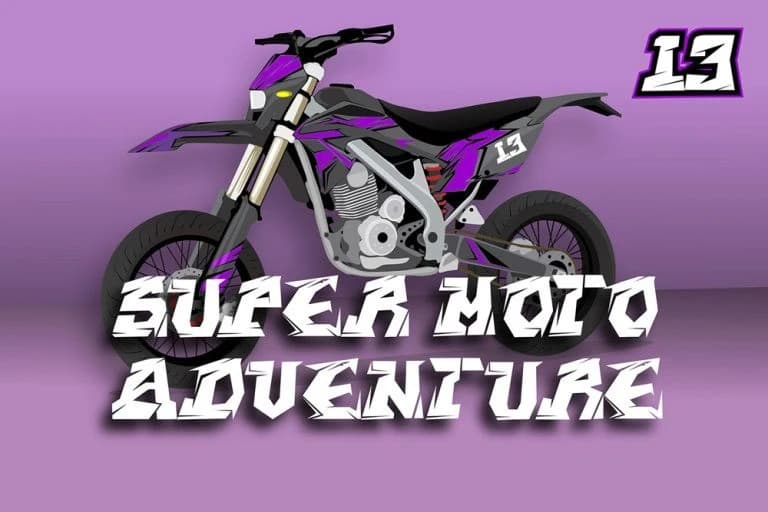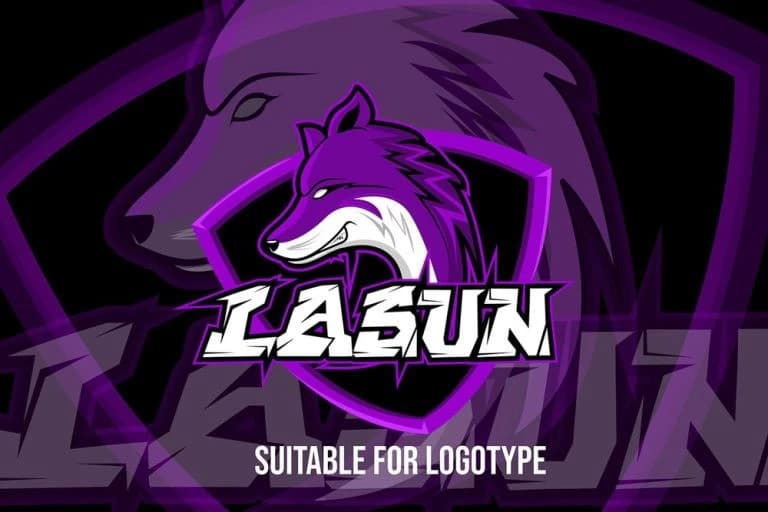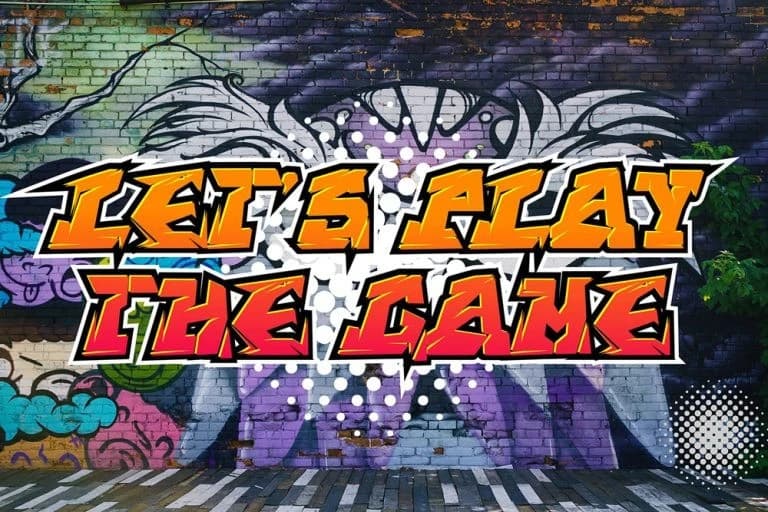
Street Wolfker Graffiti Font
Street Wolfker Graffiti Font, gelecek vaat eden vahşi grafiti yazı tipidir; cyberpunk görsellerinden, yeraltı sokak sanatından, gelecek odaklı kentsel kültürden ve agresif grafiti tipografisi trendlerinden ilham almıştır. Keskin harf biçimlerine sahip ve dinamik gelecek odaklı detaylarla tasarlanmış
Street Wolfker Graffiti Font, siberpunk görsellerinden, yeraltı sokak sanatından, gelecek odaklı kentsel kültürden ve agresif graffiti tipografisi trendlerinden ilham alan bir gelecekçi vahşi graffiti yazı tipidir. Keskin harf biçimleriyle ve dinamik gelecekçi detaylarla tasarlandı